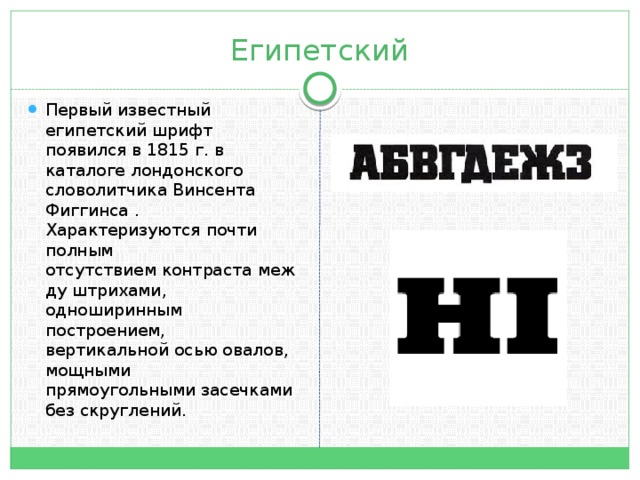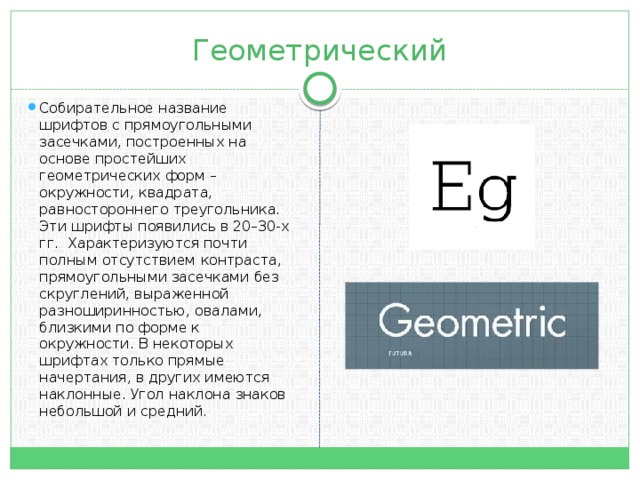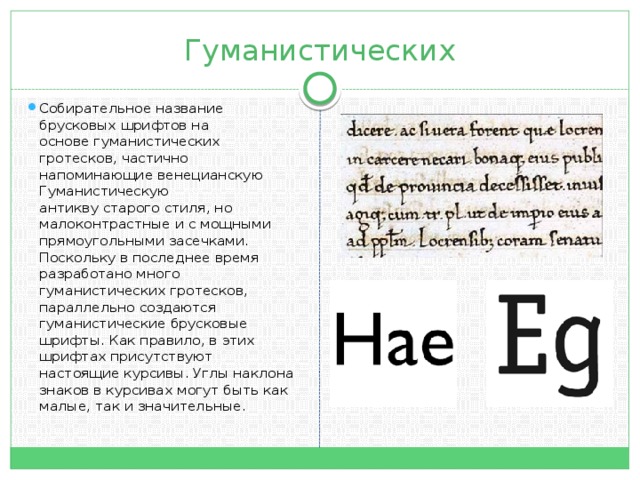
Брусковый шрифт и его виды
Мы узнаем что такое брусковый шрифт, где он появился, разберём египетский, геометрический, гуманистический шрифты, а аткже где он используется.
«Брусковый шрифт и его виды»
Брусковый шрифт
Что это такое ? Брусковый шрифт  — шрифт c мощными засечкамии прямоугольной формы без скруглений или с небольшим скруглением в местах присоединения к основным штрихам. Такие шрифты отличаются небольшим контрастом между толщиной основных и соединительных линий или полным его отсутствием.
Что это такое ?
• Брусковый шрифт  — шрифт c мощными засечкамии прямоугольной формы без скруглений или с небольшим скруглением в местах присоединения к основным штрихам. Такие шрифты отличаются небольшим контрастом между толщиной основных и соединительных линий или полным его отсутствием.
Где появился ? Первые брусковые шрифты появились в Англии в начале XIX века. В соответствии с формой овалов и засечек, наличием или отсутствием контраста и степенью разноширинности брусковые шрифты делятся на подгруппы „Египетских“, „Геометрических“, „Гуманистических“ брусковых шрифтов и брусковых шрифтов типа „Кларендон“. Кроме того, в эту группу также иногда относят брусковые шрифты с обратным контрастом „Итальянские“
Где появился ?
• Первые брусковые шрифты появились в Англии в начале XIX века. В соответствии с формой овалов и засечек, наличием или отсутствием контраста и степенью разноширинности брусковые шрифты делятся на подгруппы „Египетских“, „Геометрических“, „Гуманистических“ брусковых шрифтов и брусковых шрифтов типа „Кларендон“. Кроме того, в эту группу также иногда относят брусковые шрифты с обратным контрастом „Итальянские“
Египетский Первый известный египетский шрифт появился в 1815 г. в каталоге лондонского словолитчика Винсента Фиггинса . Характеризуются почти полным отсутствием контраста между штрихами, одноширинным построением, вертикальной осью овалов, мощными прямоугольными засечками без скруглений.
Египетский
• Первый известный египетский шрифт появился в 1815 г. в каталоге лондонского словолитчика Винсента Фиггинса . Характеризуются почти полным отсутствием контраста между штрихами, одноширинным построением, вертикальной осью овалов, мощными прямоугольными засечками без скруглений.
Геометрический Собирательное название шрифтов c прямоугольными засечками, построенных на основе простейших геометрических форм – окружности, квадрата, равностороннего треугольника. Эти шрифты появились в 20–30-х гг. Характеризуются почти полным отсутствием контраста, прямоугольными засечками без скруглений, выраженной разноширинностью, овалами, близкими по форме к окружности. В некоторых шрифтах только прямые начертания, в других имеются наклонные. Угол наклона знаков небольшой и средний.
Геометрический
• Собирательное название шрифтов c прямоугольными засечками, построенных на основе простейших геометрических форм – окружности, квадрата, равностороннего треугольника. Эти шрифты появились в 20–30-х гг. Характеризуются почти полным отсутствием контраста, прямоугольными засечками без скруглений, выраженной разноширинностью, овалами, близкими по форме к окружности. В некоторых шрифтах только прямые начертания, в других имеются наклонные. Угол наклона знаков небольшой и средний.
Гуманистических Собирательное название брусковых шрифтов на основе гуманистических гротесков, частично напоминающие венецианскую Гуманистическую антикву старого стиля, но малоконтрастные и с мощными прямоугольными засечками. Поскольку в последнее время разработано много гуманистических гротесков, параллельно создаются гуманистические брусковые шрифты. Как правило, в этих шрифтах присутствуют настоящие курсивы. Углы наклона знаков в курсивах могут быть как малые, так и значительные.
Гуманистических
• Собирательное название брусковых шрифтов на основе гуманистических гротесков, частично напоминающие венецианскую Гуманистическую антикву старого стиля, но малоконтрастные и с мощными прямоугольными засечками. Поскольку в последнее время разработано много гуманистических гротесков, параллельно создаются гуманистические брусковые шрифты. Как правило, в этих шрифтах присутствуют настоящие курсивы. Углы наклона знаков в курсивах могут быть как малые, так и значительные.
Где используется ? Шрифты этого типа занимают ведущее место по шкале читабельности и идеально подходят для набора длинных текстов, так как имеют очень слабый контраст. Однако страница, набранная этим шрифтом, выглядит значитель­но «темнее» страницы, набранной обычной гарнитурой, поскольку штри­хи брускового типа плотнее и более единообразны по толщине. Брусковый шрифт ча­сто используется при наборе детских книг.
Где используется ?
• Шрифты этого типа занимают ведущее место по шкале читабельности и идеально подходят для набора длинных текстов, так как имеют очень слабый контраст. Однако страница, набранная этим шрифтом, выглядит значитель­но «темнее» страницы, набранной обычной гарнитурой, поскольку штри­хи брускового типа плотнее и более единообразны по толщине. Брусковый шрифт ча­сто используется при наборе детских книг.